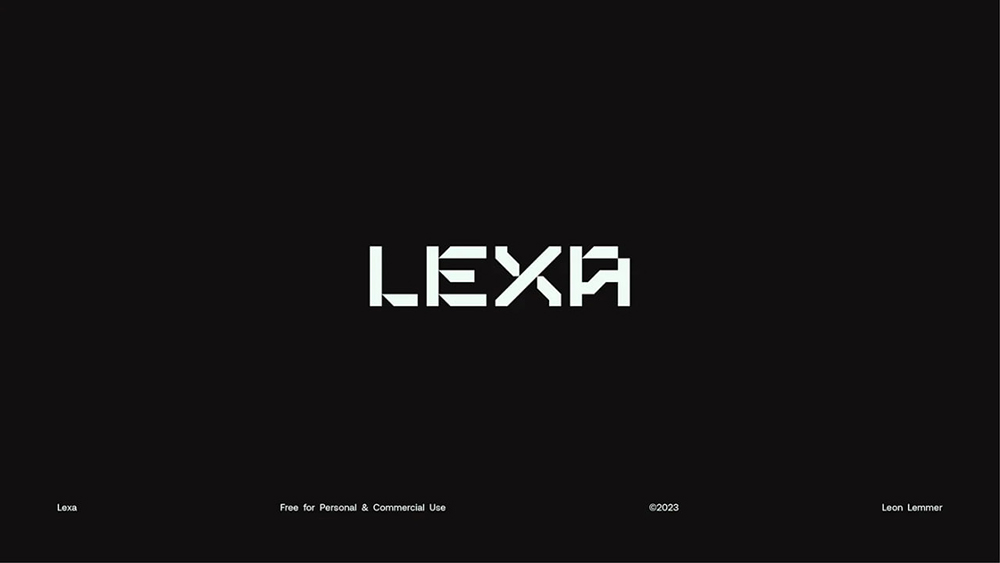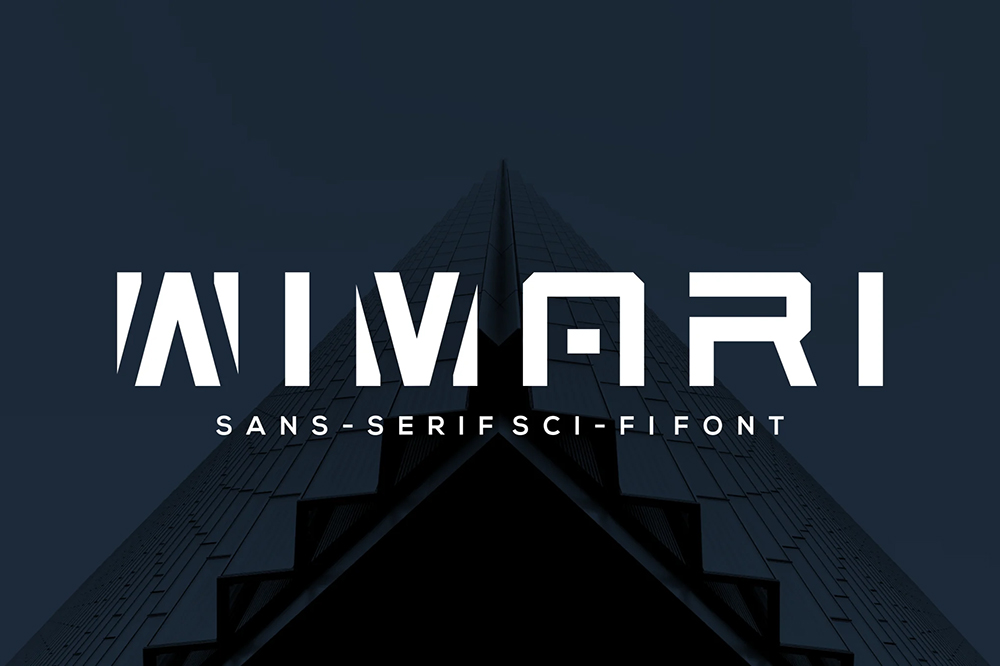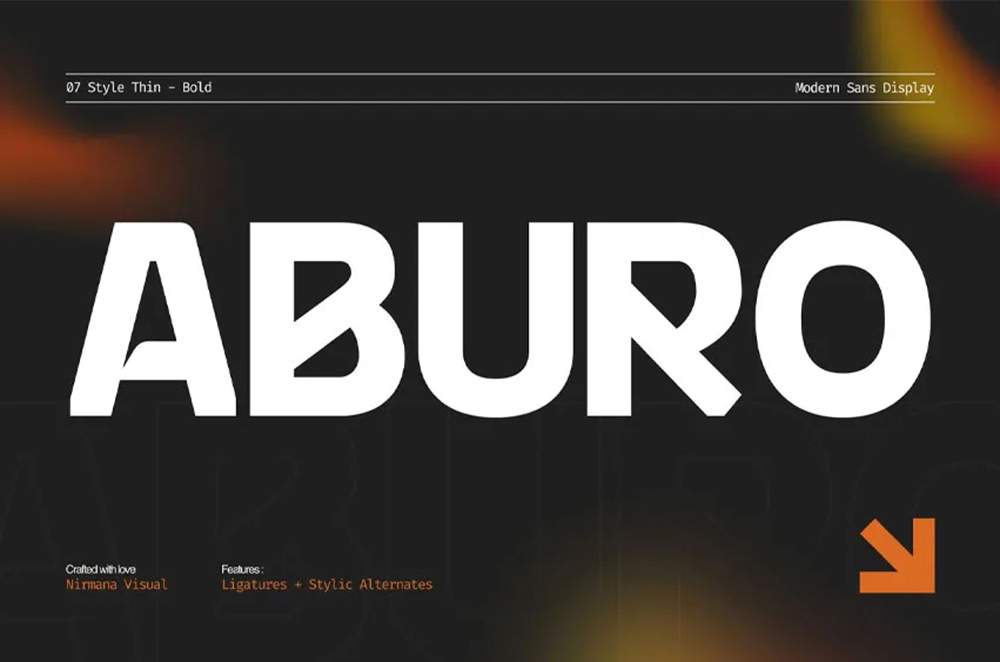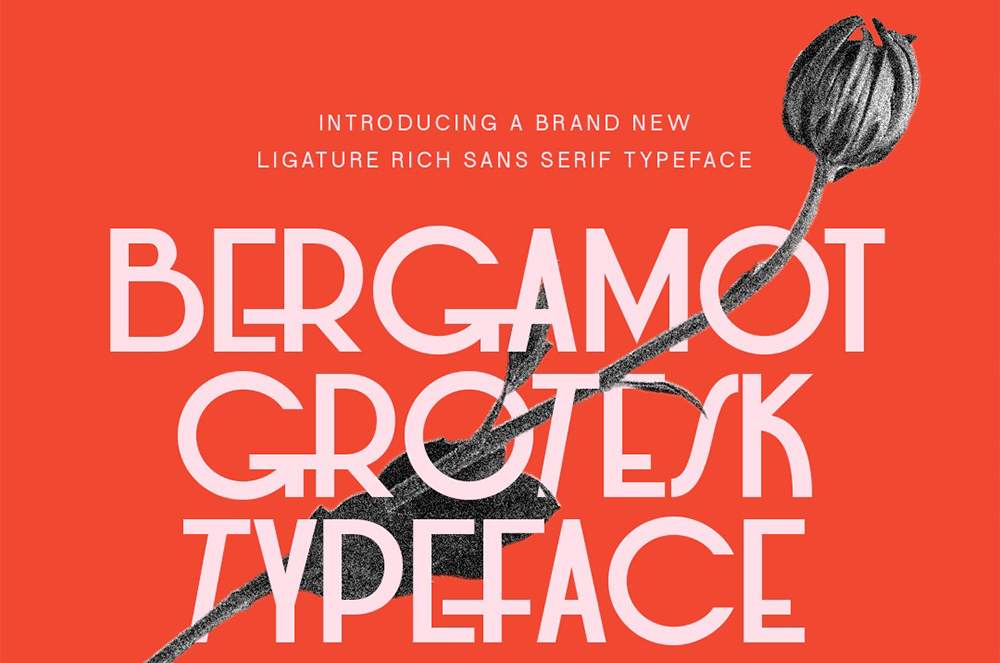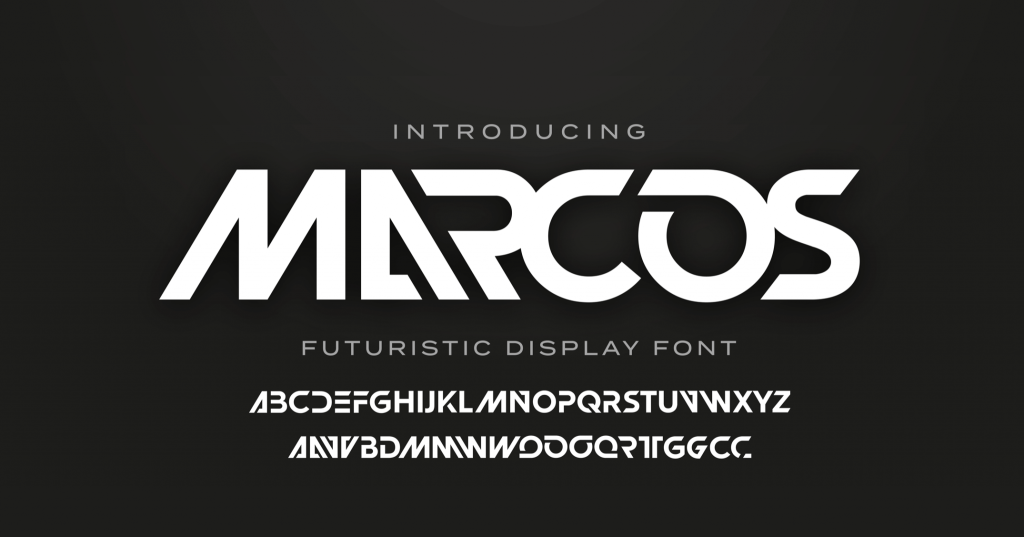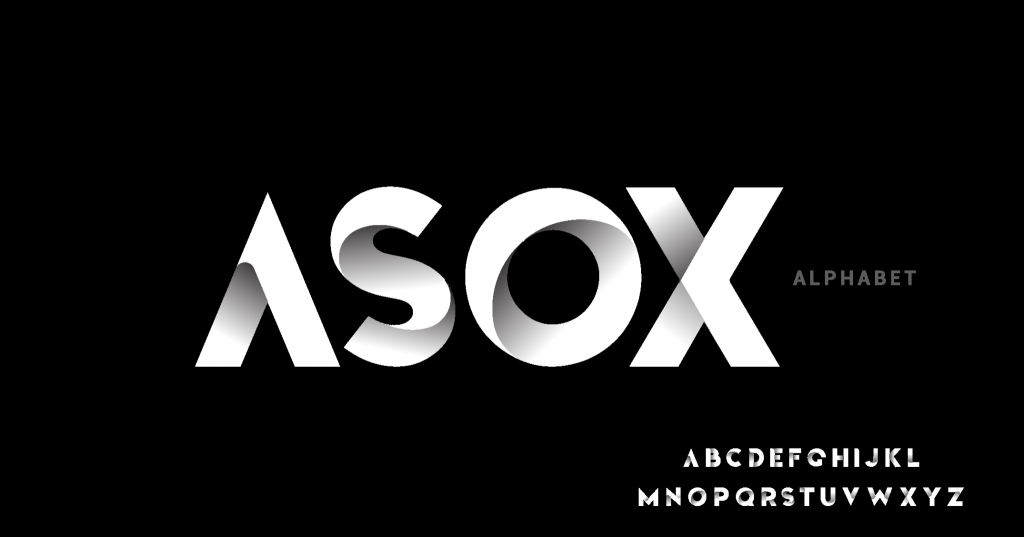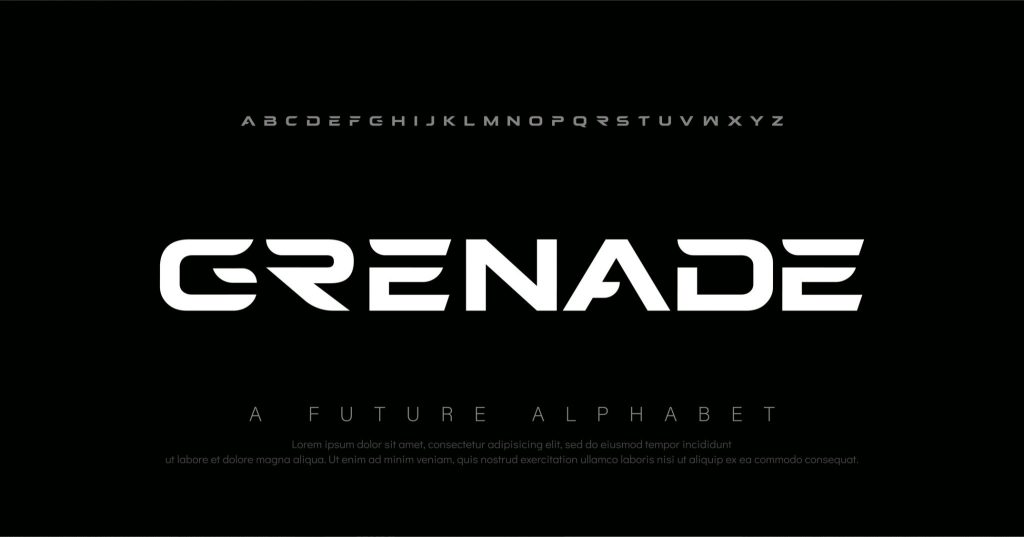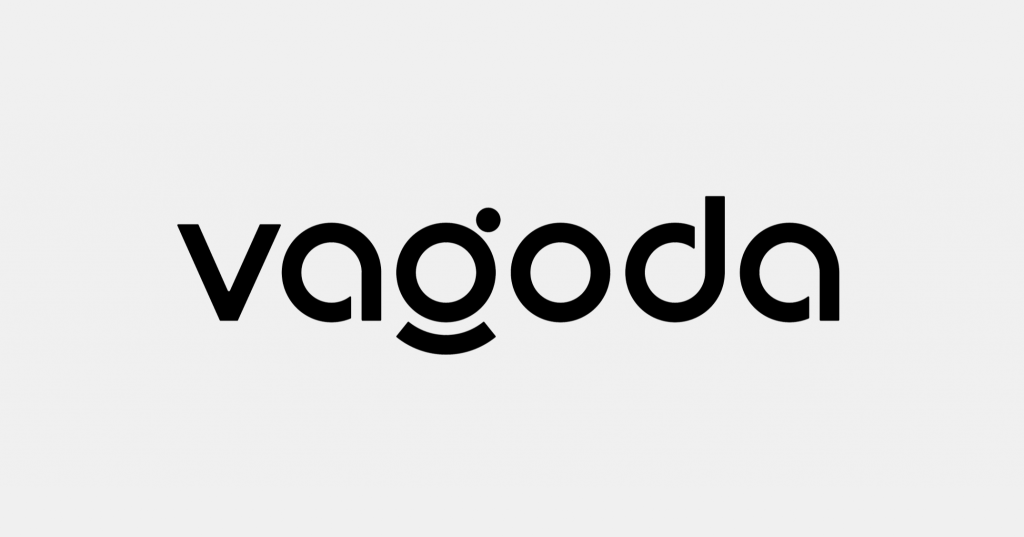
بهترین فونتهای انگلیسی برای طراحی لوگو در بین این همه فونت انگلیسی کدام فونتها هستند؟
تصور کنید یک برند بسیار لوکس و گرانقیمت را در نظر بگیرید، اما نام آن با یک فونت ساده، بیروح و ابتدایی مثل Comic Sans نوشته شده باشد! چه حسی به شما دست میدهد؟ احتمالاً بلافاصله اعتماد خود را به آن برند از دست میدهید.
در دنیای طراحی گرافیک، فونتها فقط مجموعهای از حروف نیستند؛ آنها “صدای بصری” برند هستند. یک فونت اشتباه میتواند تمام زحمات شما برای طراحی آیکون و انتخاب پالت رنگی را به باد دهد. بسیاری از گرافیستها و طراحان در ابتدای مسیر، با این چالش روبرو میشوند که: «چطور بفهمم این فونت با شخصیت برند همخوانی دارد؟» یا «کدام فونتها استاندارد جهانی برای لوگوهای مدرن هستند؟»
در این مقاله جامع از سایت دیاکوگرافیک، قرار است به اعماق دنیای تایپوگرافی سفر کنیم، یاد بگیریم چطور فونت مناسب را انتخاب کنیم و در نهایت، لیستی از بهترین فونتهای انگلیسی برای طراحی لوگو را بررسی کنیم. پس با ما همراه باشید.
چرا انتخاب فونت درست، سرنوشت یک برند را تغییر میدهد؟
قبل از اینکه سراغ معرفی فونتها برویم، باید بدانید که انتخاب فونت (Typography Selection) یکی از ستونهای اصلی برندینگ (Branding) است. فونتها مستقیماً بر روانشناسی مخاطب اثر میگذارند.
۱. انتقال شخصیت برند (Brand Personality)
اگر برند شما یک شرکت تکنولوژی است، نیاز به فونتهای بدون سری (Sans-Serif) با خطوط تمیز و مدرن دارید. اما اگر یک برند آرایشی و بهداشتی با رویکرد کلاسیک است، فونتهای سری (Serif) یا اسکریپت (Script) بسیار مناسبتر خواهند بود.
۲. خوانایی و تشخیصپذیری (Legibility & Readability)
یک لوگو ممکن است در یک بیلبورد بزرگ در خیابان باشد یا در یک آیکون بسیار کوچک اپلیکیشن موبایل. فونت انتخابی شما باید در هر دو حالت، بدون فشار آوردن به چشم مخاطب، به راحتی خوانده شود.
۳. ایجاد تمایز در بازار
در دنیای پر از برند، فونتهای خاص و اختصاصی به شما کمک میکنند تا از نظر بصری از رقبا متمایز شوید.
راهنمای گامبهگام انتخاب فونت مناسب برای لوگو
برای اینکه در انتخاب فونت دچار اشتباه نشوید، این فرآیند مهندسیشده را دنبال کنید:
مرحله اول: تحلیل شخصیت برند
قبل از باز کردن نرمافزار ایلاستریتور، از خودتان بپرسید: برند من چگونه است؟ (مدرن یا سنتی؟ گرانقیمت یا اقتصادی؟ جسور یا آرام؟). این پاسخ، مسیر شما را در میان هزاران فونت مشخص میکند.
مرحله دوم: شناخت دستهبندیهای اصلی فونت
– Serif (سری): دارای لبههای کوچک در انتها. حس اعتماد، سنت و اصالت را منتقل میکند (مثل برند Vogue).
– Sans-Serif (بدون سری): مدرن، تمیز و مینیمال. برای برندهای تکنولوژی و استارتاپها عالی است (مثل برند Google).
– Script (دستنویس): حس ظرافت، خلاقیت و شخصی بودن دارد (مناسب برای برندهای لوکس و آرایشی).
– Display (نمایشی): فونتهای بسیار خاص و عجیب که برای تیترهای بزرگ و لوگوهای بسیار متمایز به کار میروند.
مرحله سوم: تست در ابعاد مختلف
همیشه لوگوی خود را در اندازه بسیار کوچک و بسیار بزرگ تست کنید. اگر فونت در اندازه کوچک به هم ریخت، یعنی آن فونت برای لوگو مناسب نیست.
بررسی موردی: استراتژی فونت در برندهای جهانی
بیایید نگاهی بیندازیم به برندهایی که با انتخاب فونت، جایگاه خود را تثبیت کردهاند:
– برند Netflix: نتفلیکس از یک فونت اختصاصی به نام Netflix Sans استفاده میکند. این فونت به گونهای طراحی شده که در تمام پلتفرمها (از تلویزیون تا گوشی) بسیار خوانا باشد و حس هیجان و مدرنیته را منتقل کند.
– برند Coca-Cola: این برند از یک فونت اسکریپت (دستنویس) بسیار خاص استفاده میکند که نماد سنت، شادی و راحتی است. این فونت آنقدر با برند گره خورده که حتی بدون خواندن کلمه، شما برند را میشناسید.
در ایران نیز، برندهای بزرگ از فونتهای اختصاصی استفاده میکنند تا در بازار شلوغ، هویت بصری متمایزی داشته باشند.
و حالا به بررسی ده تا بهترین فونتهای انگلیسی برای طراحی لوگو خواهیم پرداخت:
معرفی بهترین فونتهای انگلیسی برای طراحی لوگو
1-فونت انگلیسی لوگو موشن Logo Motion English Font
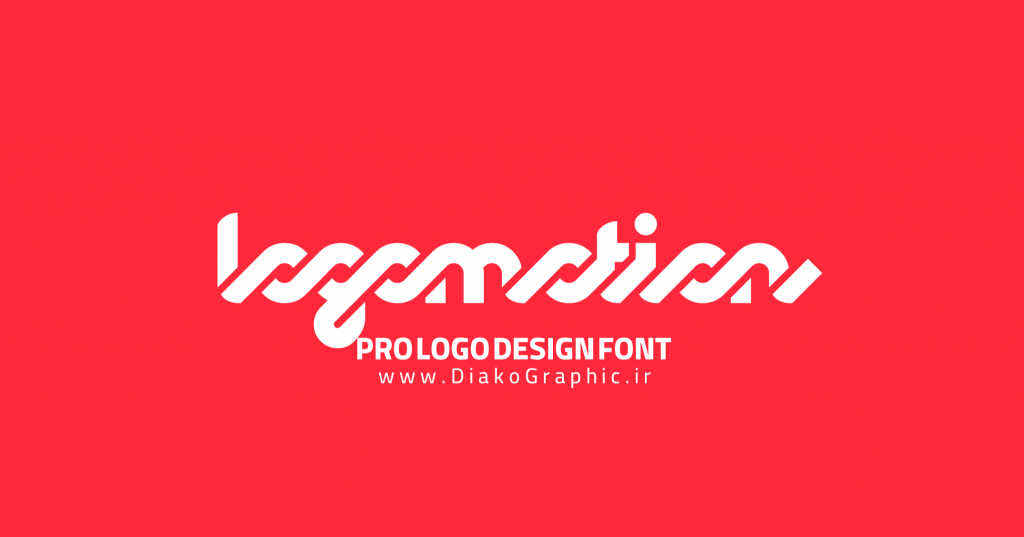
فونتهای لوگوتایپ معمولاً ویژگیهای بصری منحصربهفردی دارند که برای استفاده در تیترها و نشانها بهینه شدهاند و اجازه میدهند طراح کنترل بیشتری روی فرم و ساختار حروف داشته باشد.
۴. آیا فونت انگلیسی برای برندهای ایرانی هم مناسب است؟
بله، اگر مخاطب هدف شما بینالمللی است یا برند شما ماهیت مدرن و جهانی دارد، استفاده از تایپوگرافی انگلیسی در کنار المانهای دیگر بسیار رایج و حرفهای است.